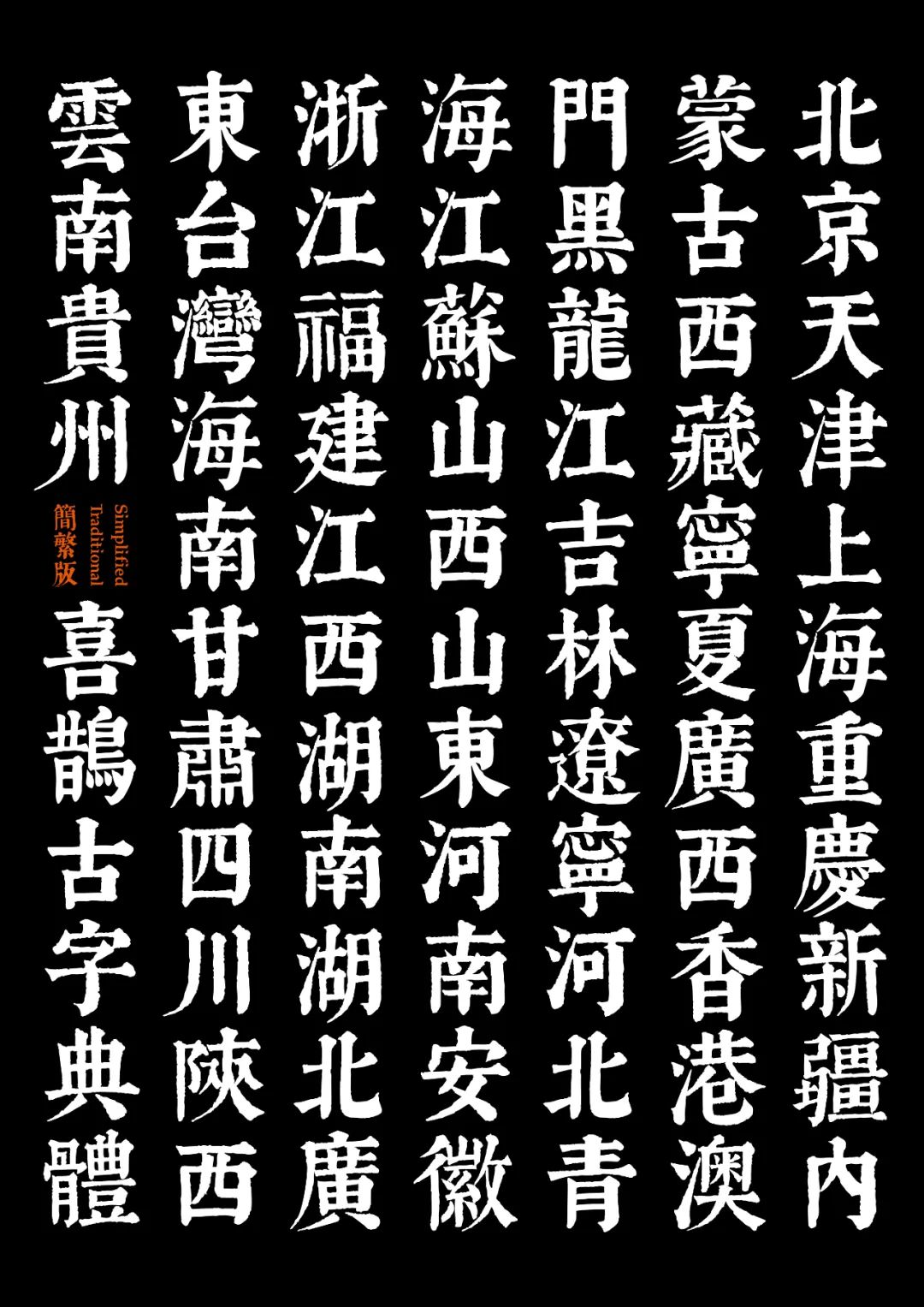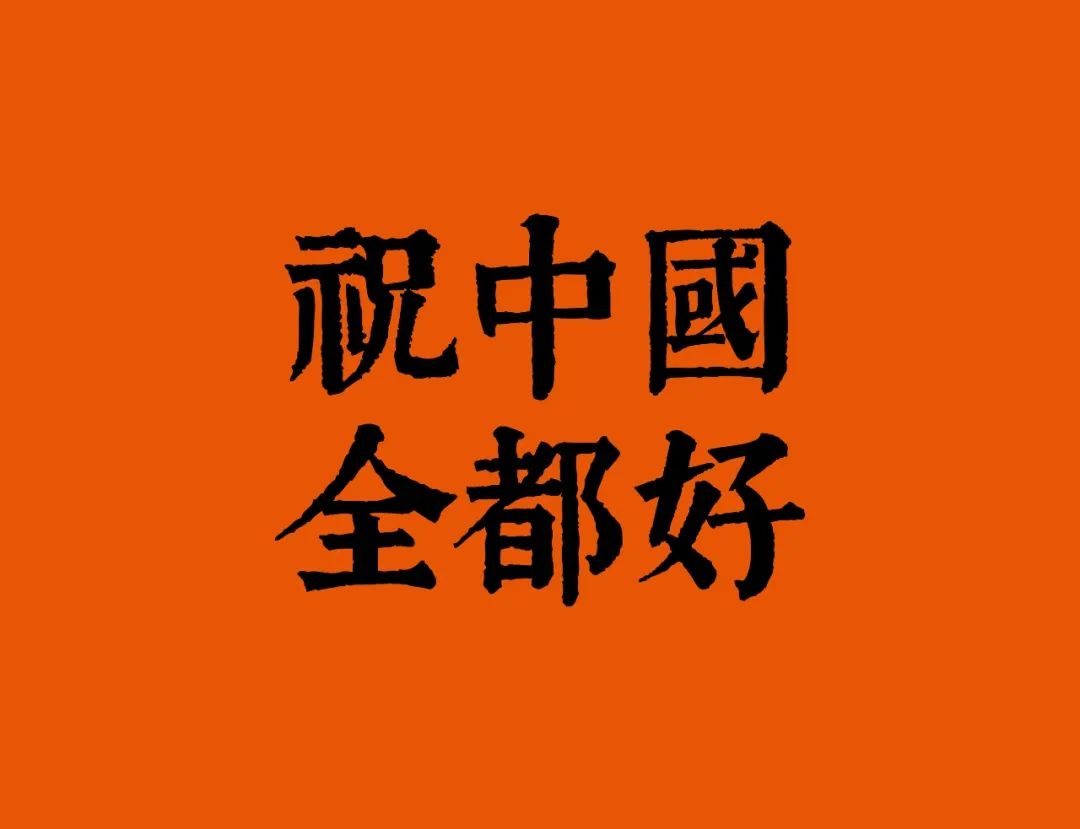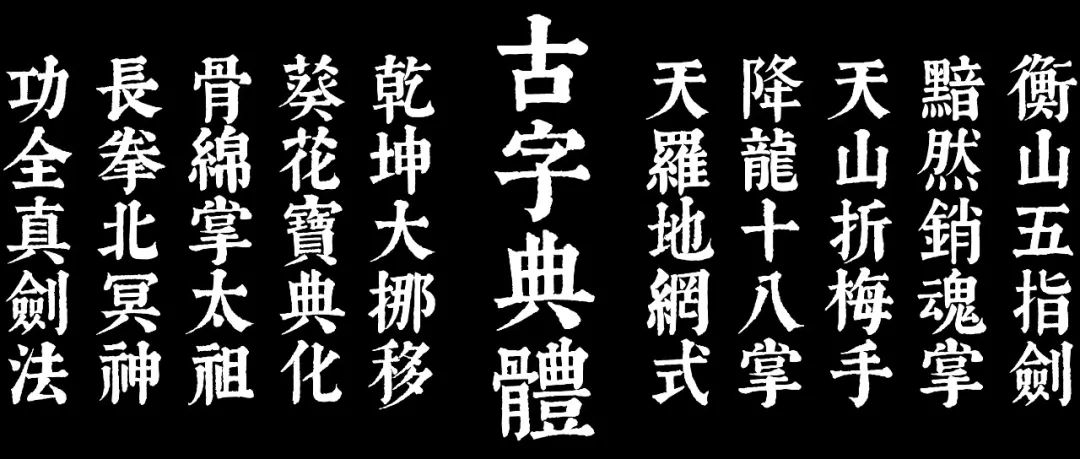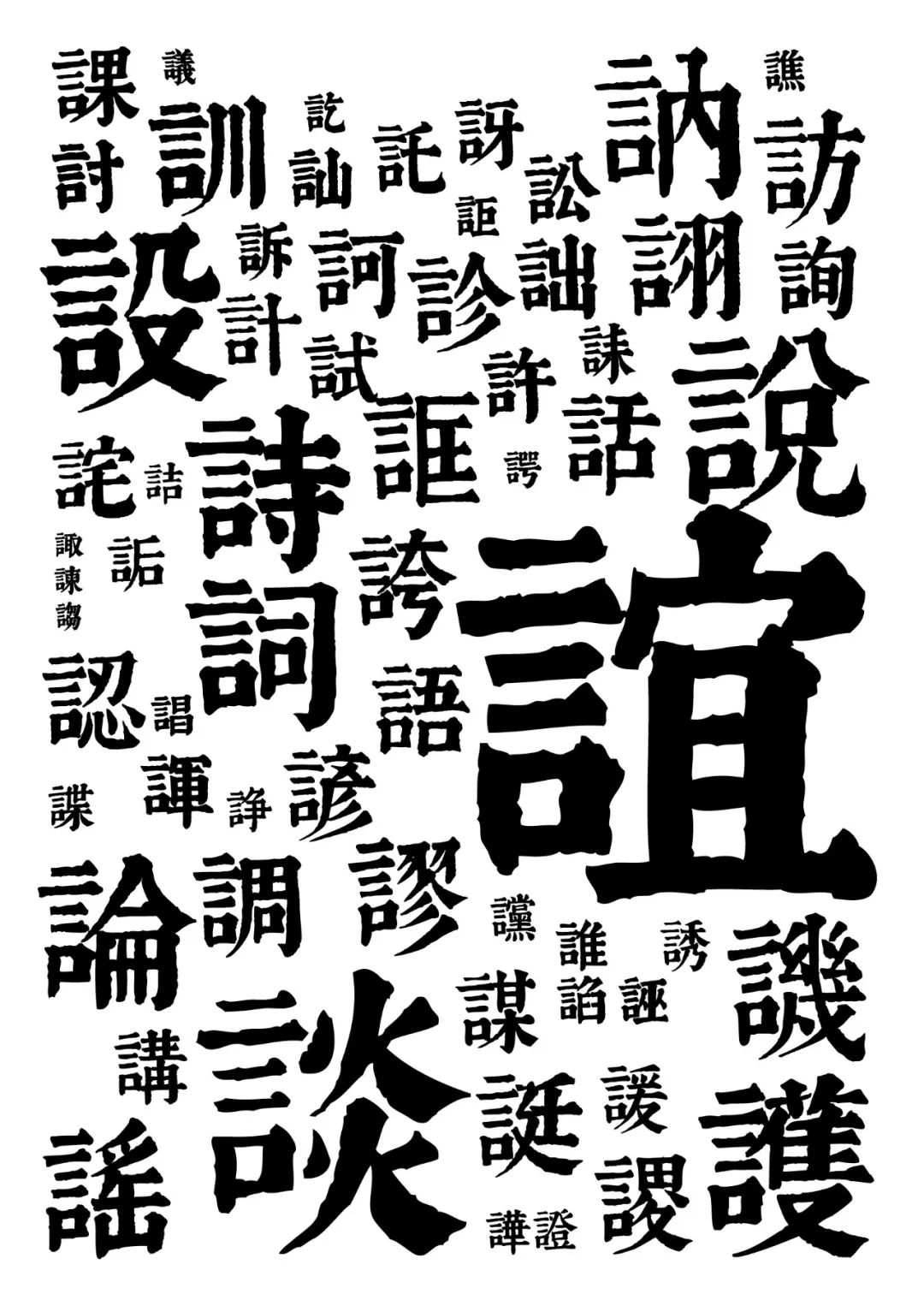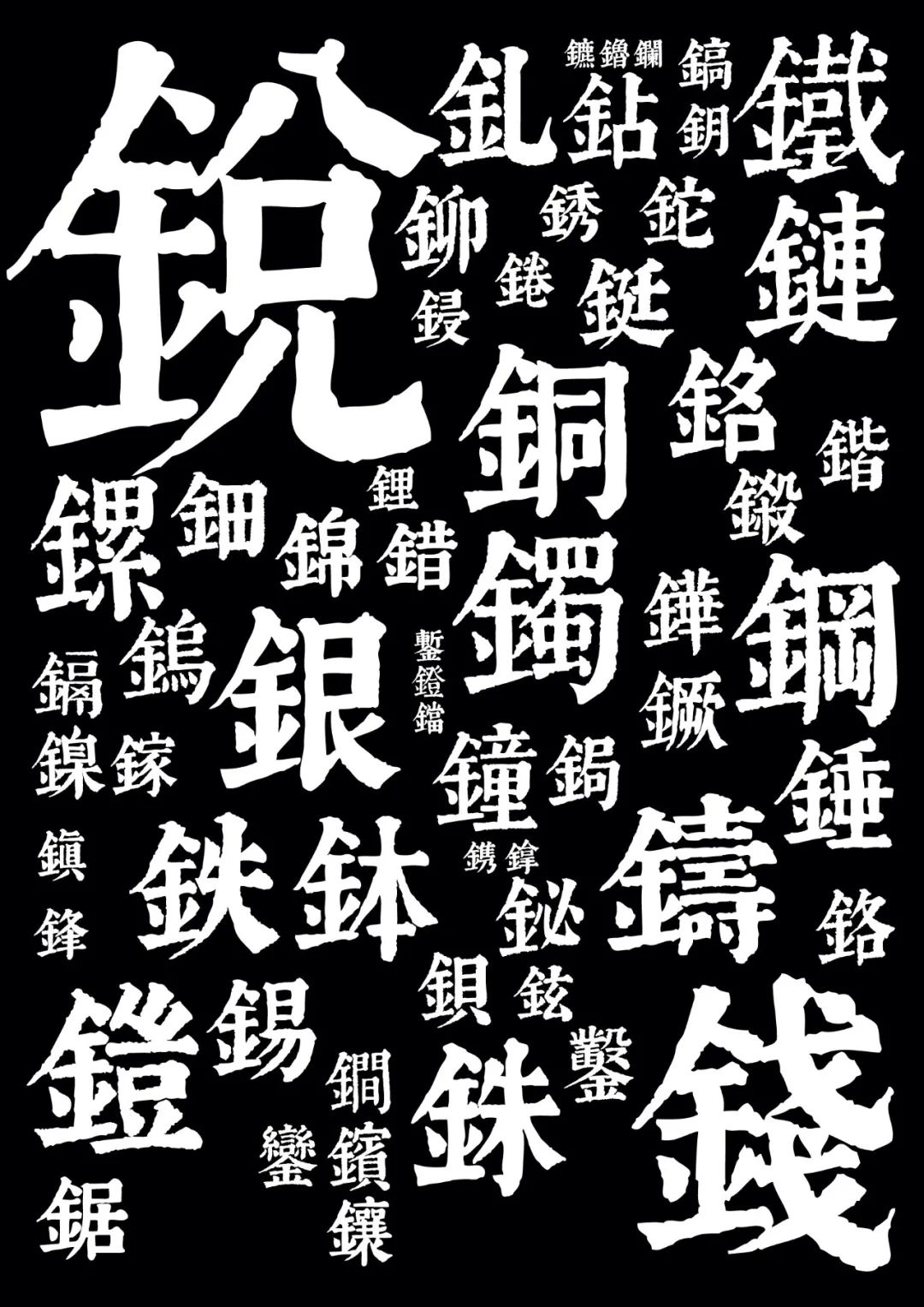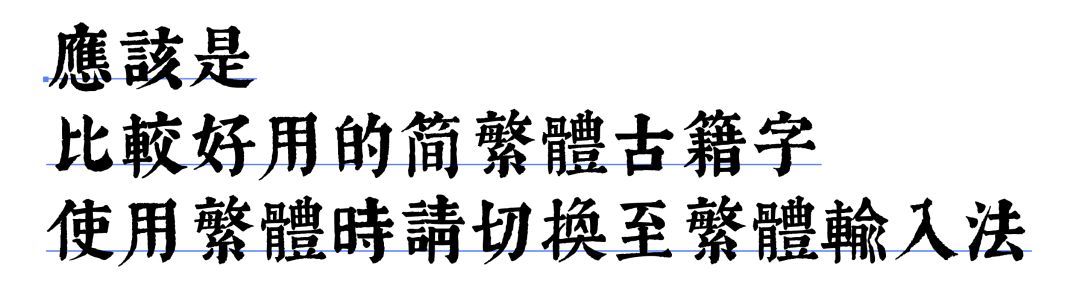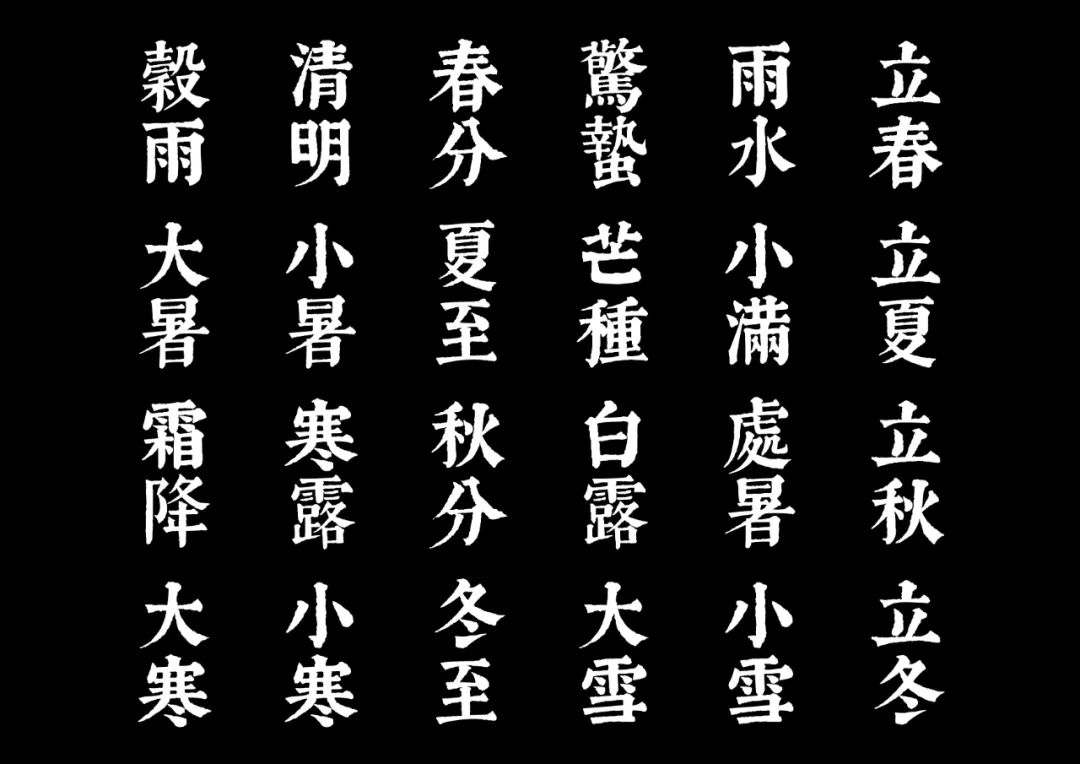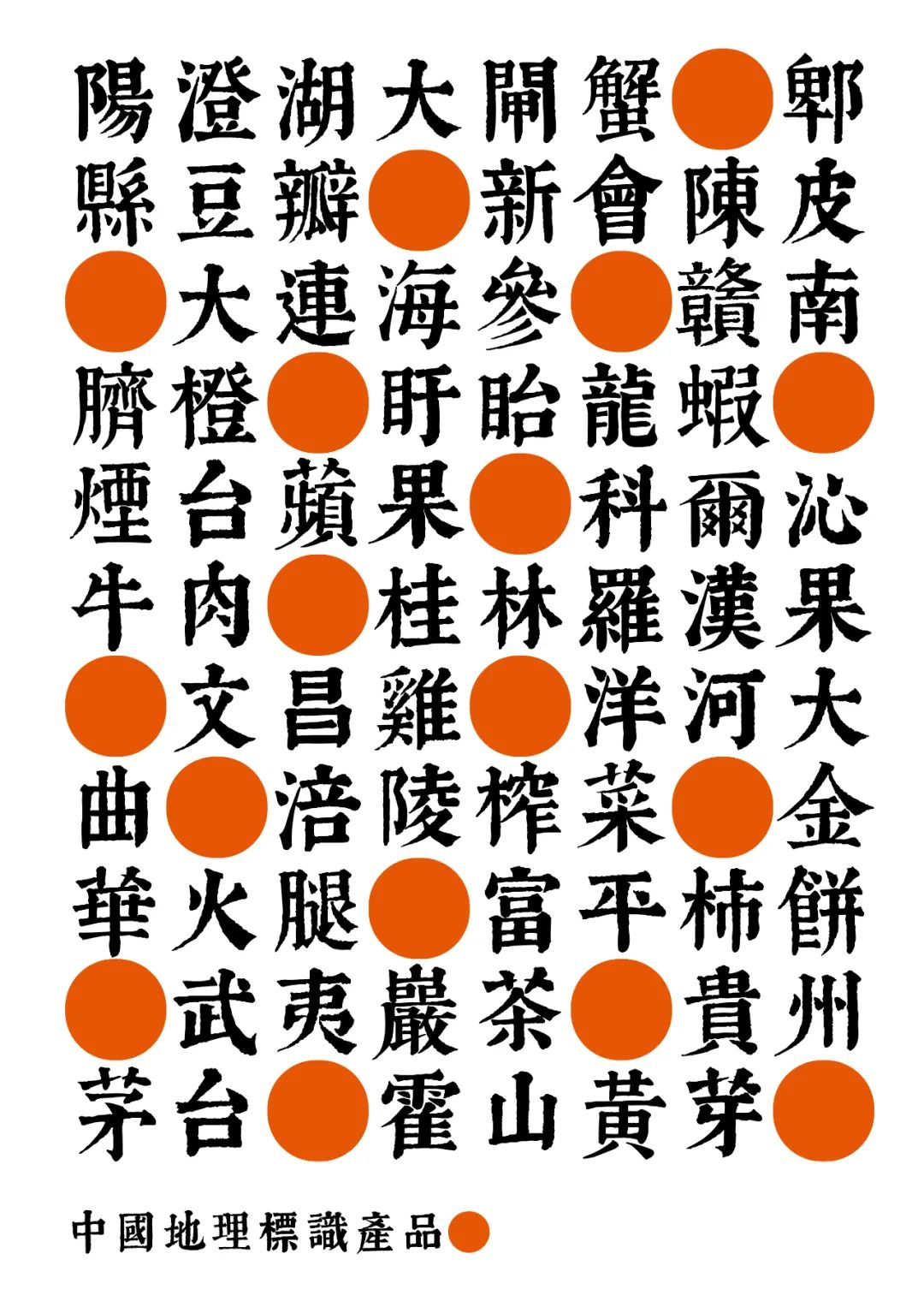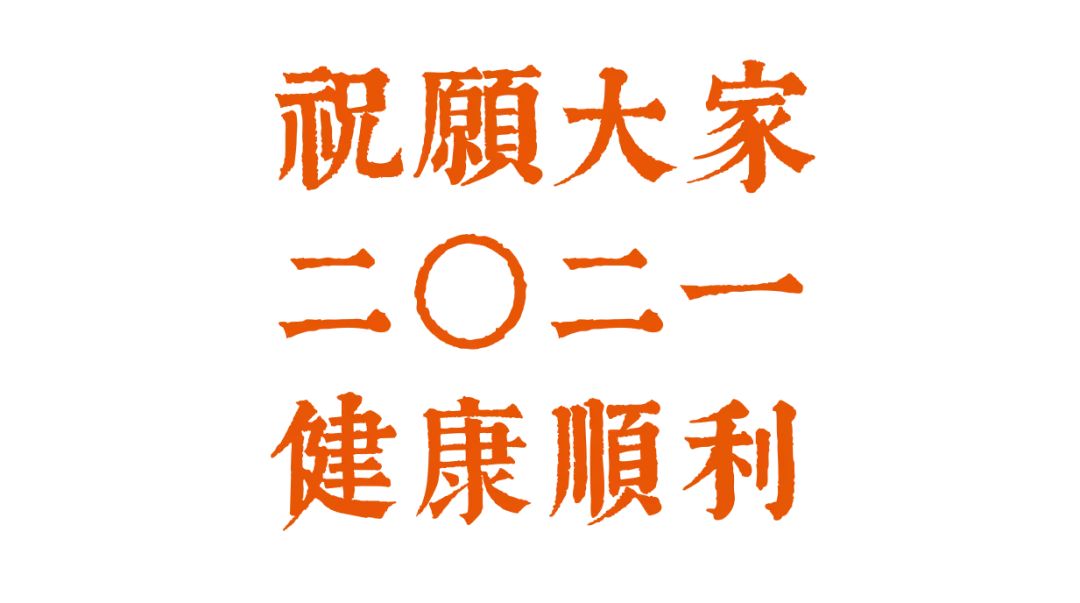
喜鹊古字典体 |喜鹊造字2021新字古字典体简繁大字库上线!
喜鹊古字典体新增补繁体!
古字典体(简+繁体)版大字库 正式上线!
喜鹊古字典体(简+繁体)版大字库
字体介绍:喜鹊古字典体,集字&摩字于明末清初著名的字典《正字通》。字形朴实、细节有力。制作数字字形时 追求还原古籍原味,保留描摹时的斑驳轮廓而成。稳重中多一些侠义之感。
适用于:中式味道偏复古的标志标题等文字需求,如中式餐饮、文创品牌、古典诗词、小说、食品文化、古风影视等。
于Glyphs开发制作当中:
字体展示: